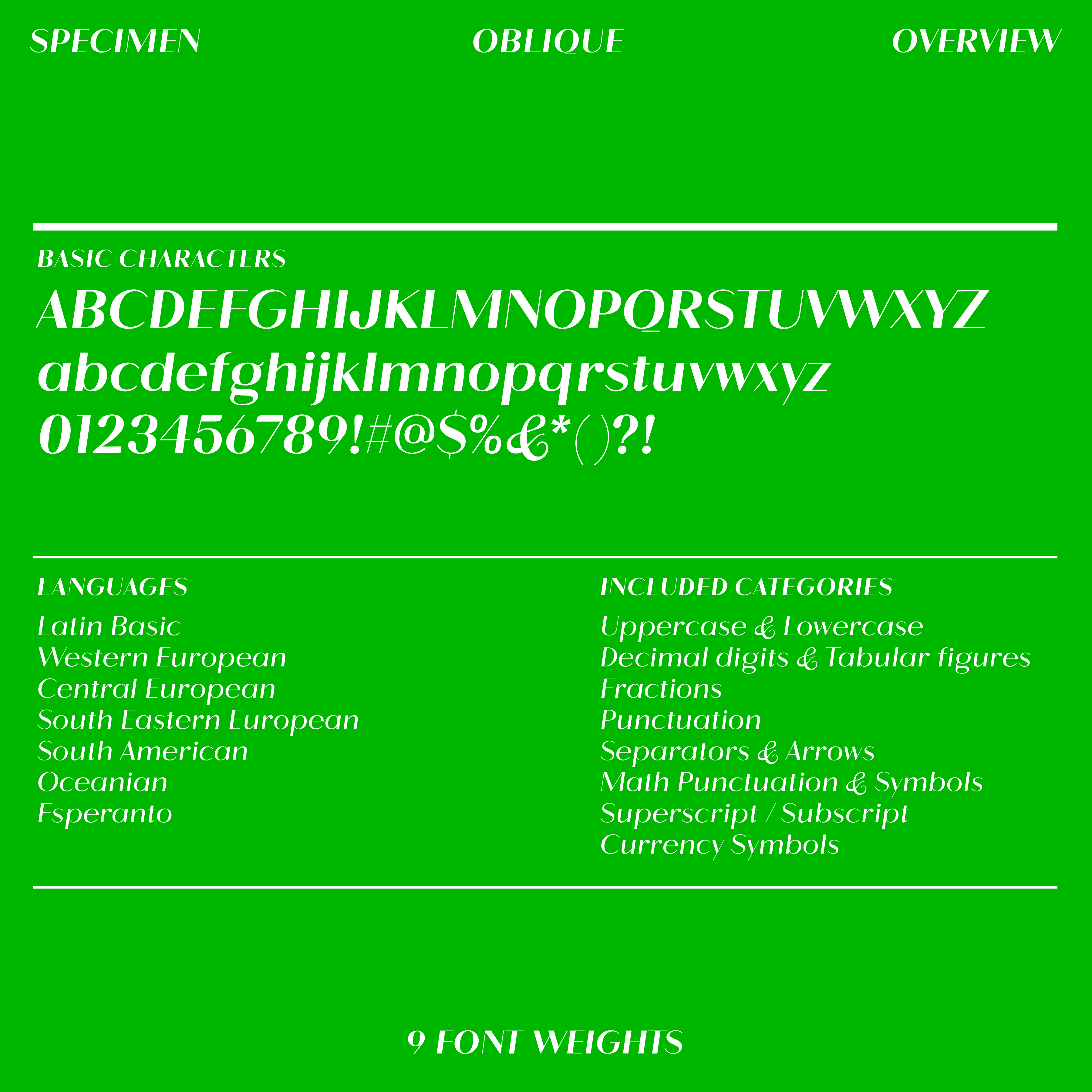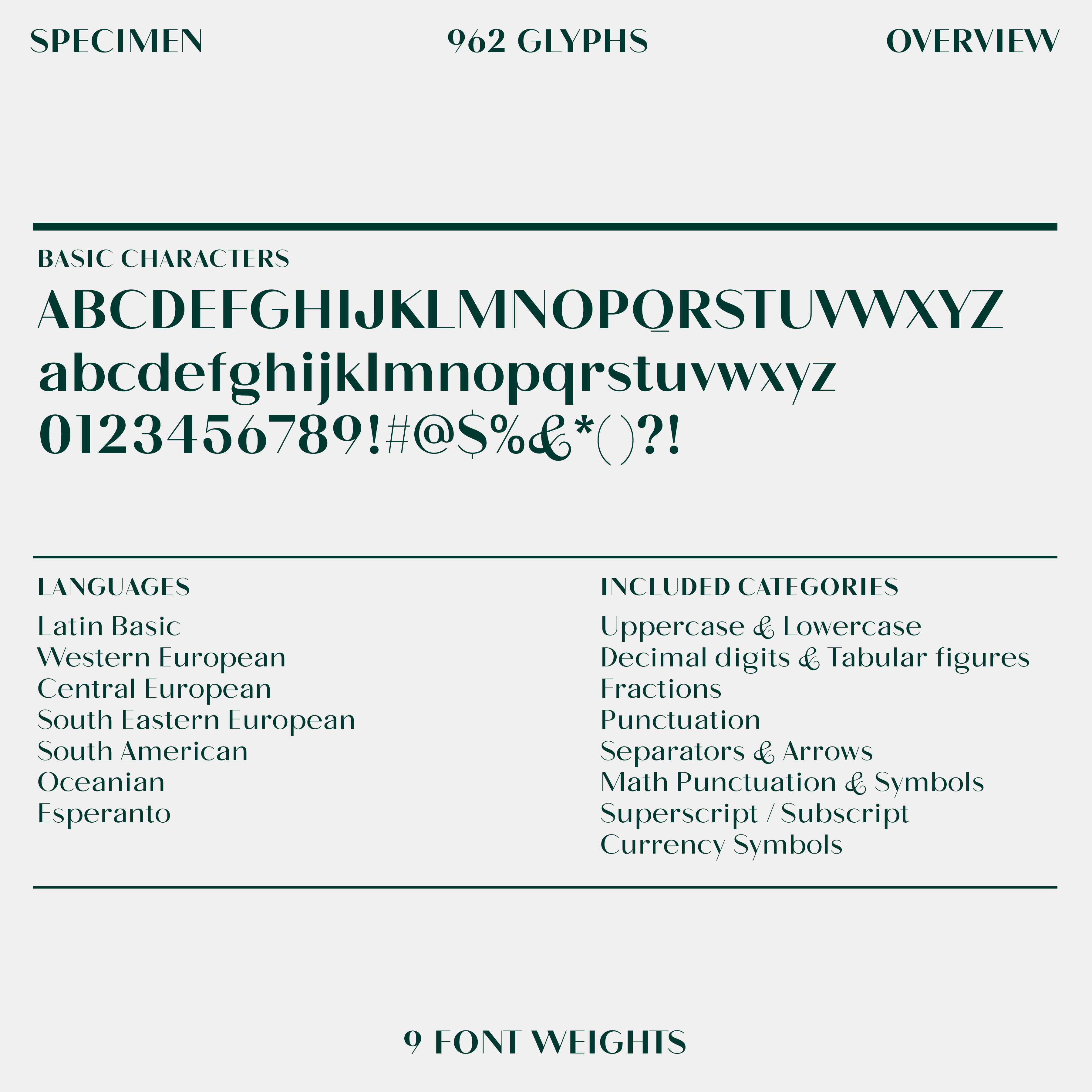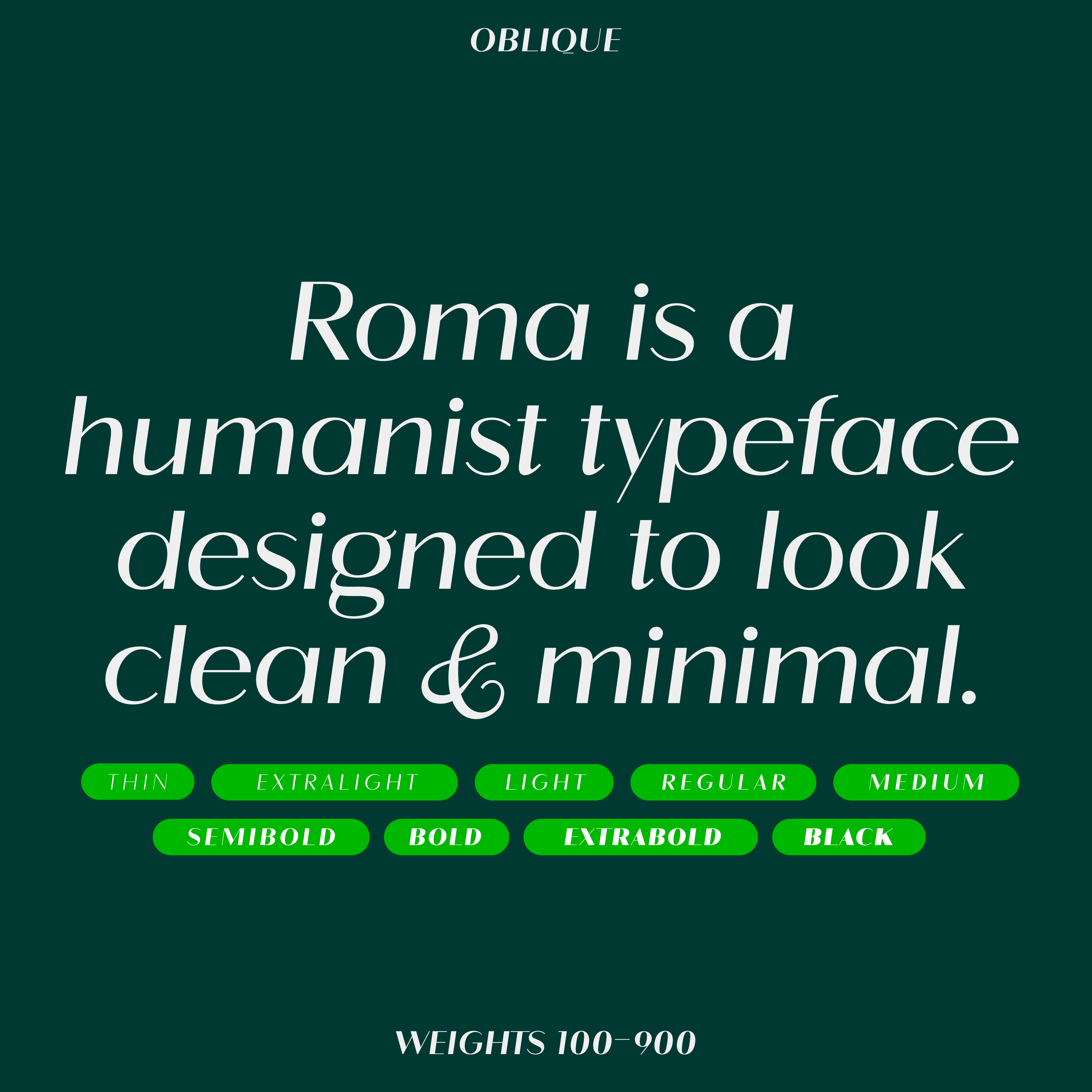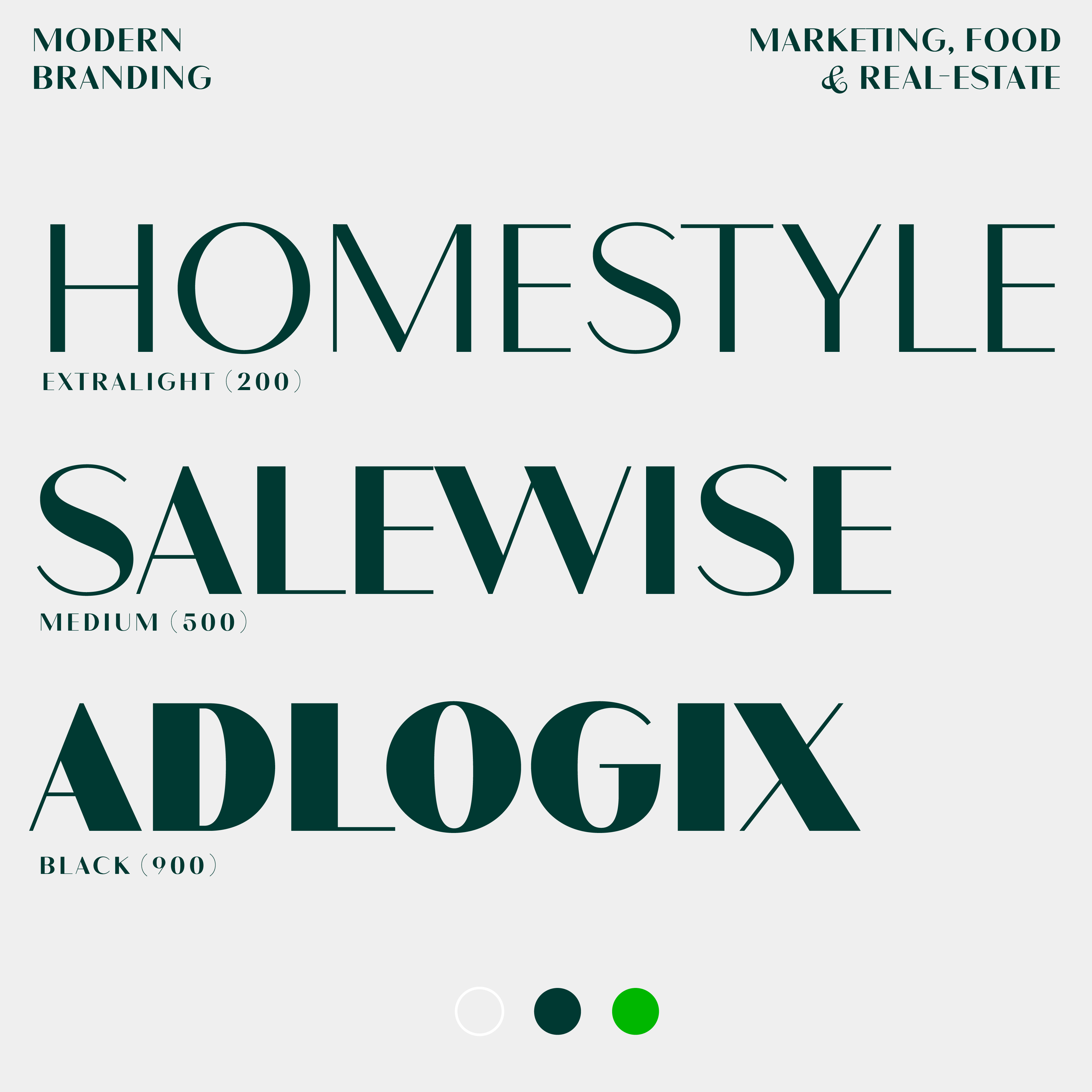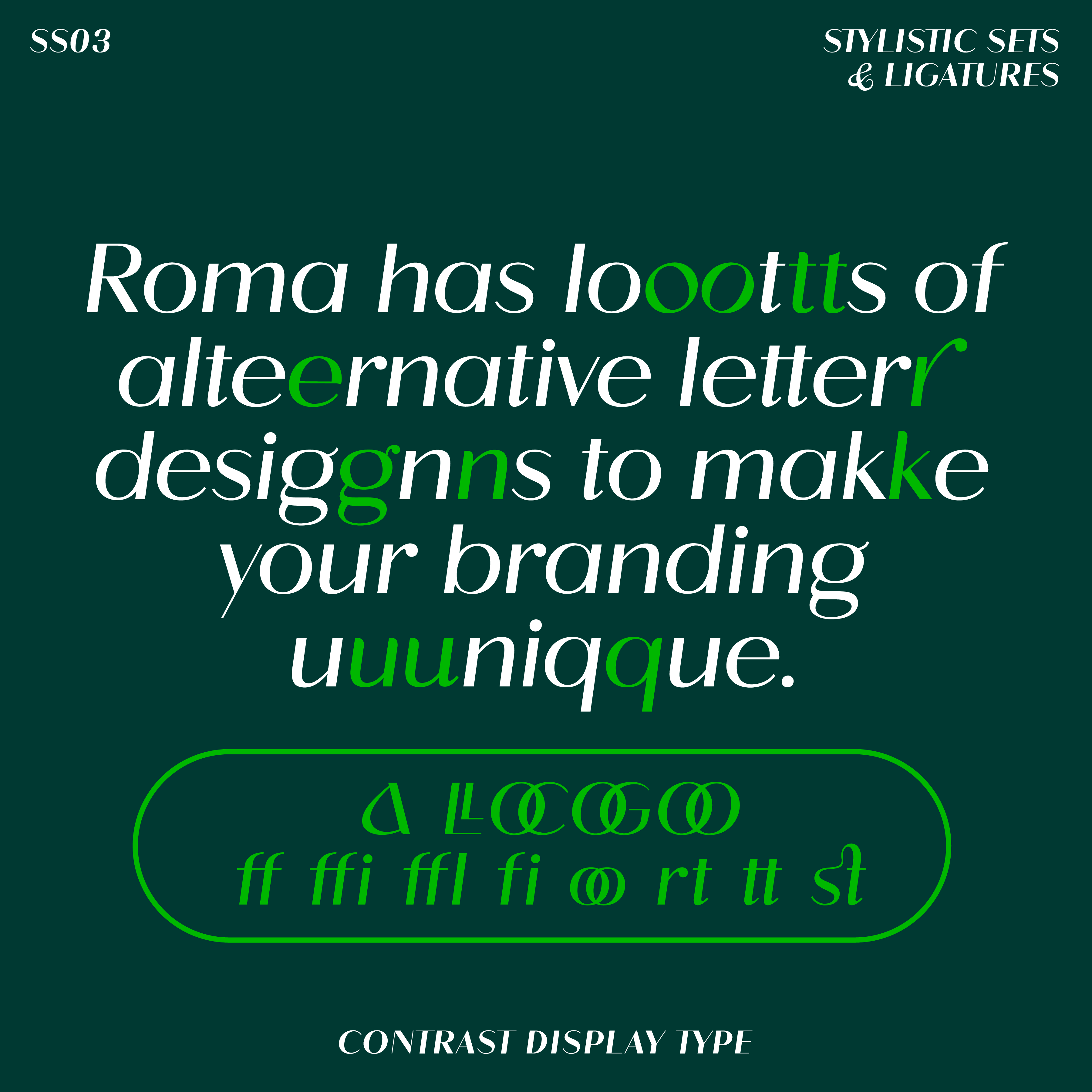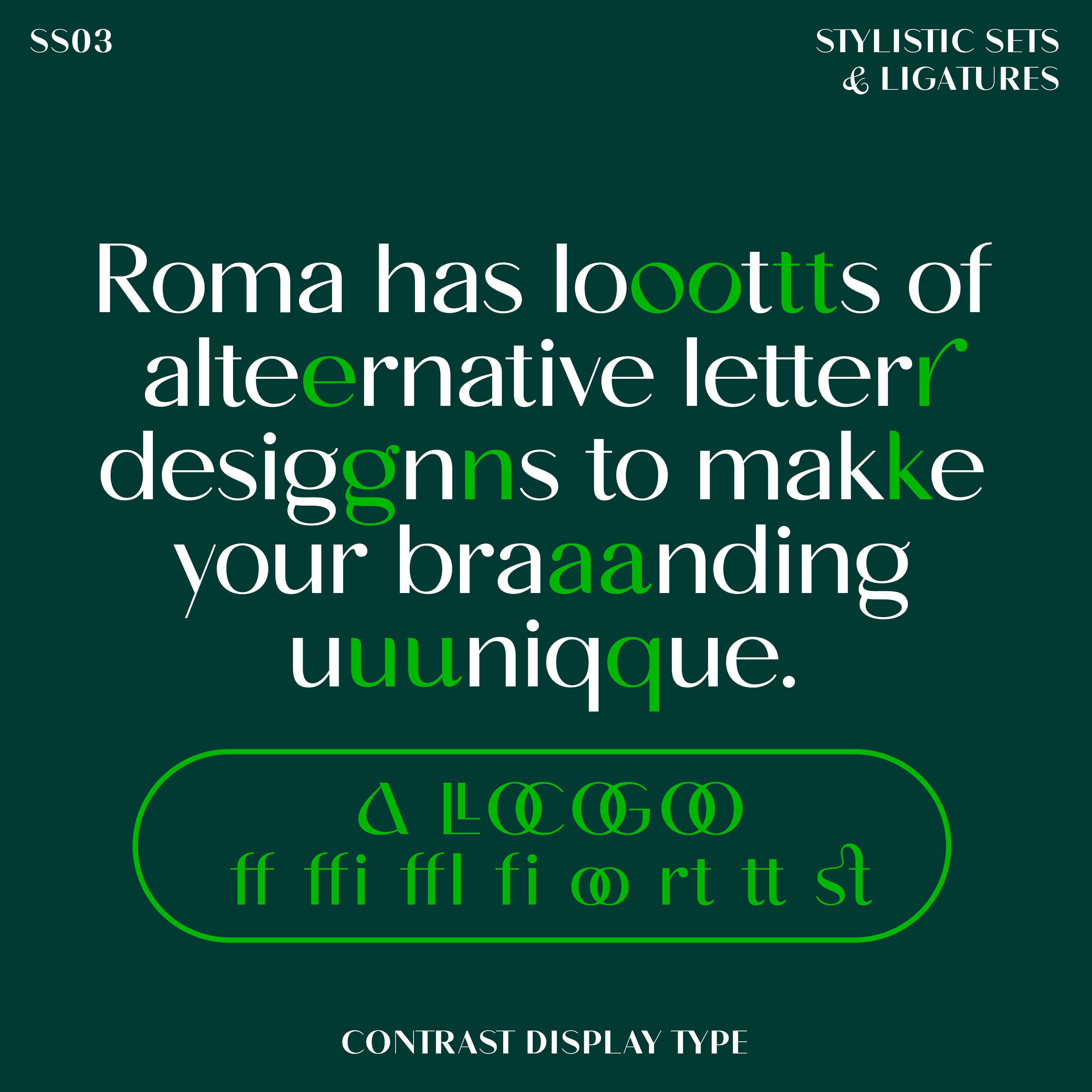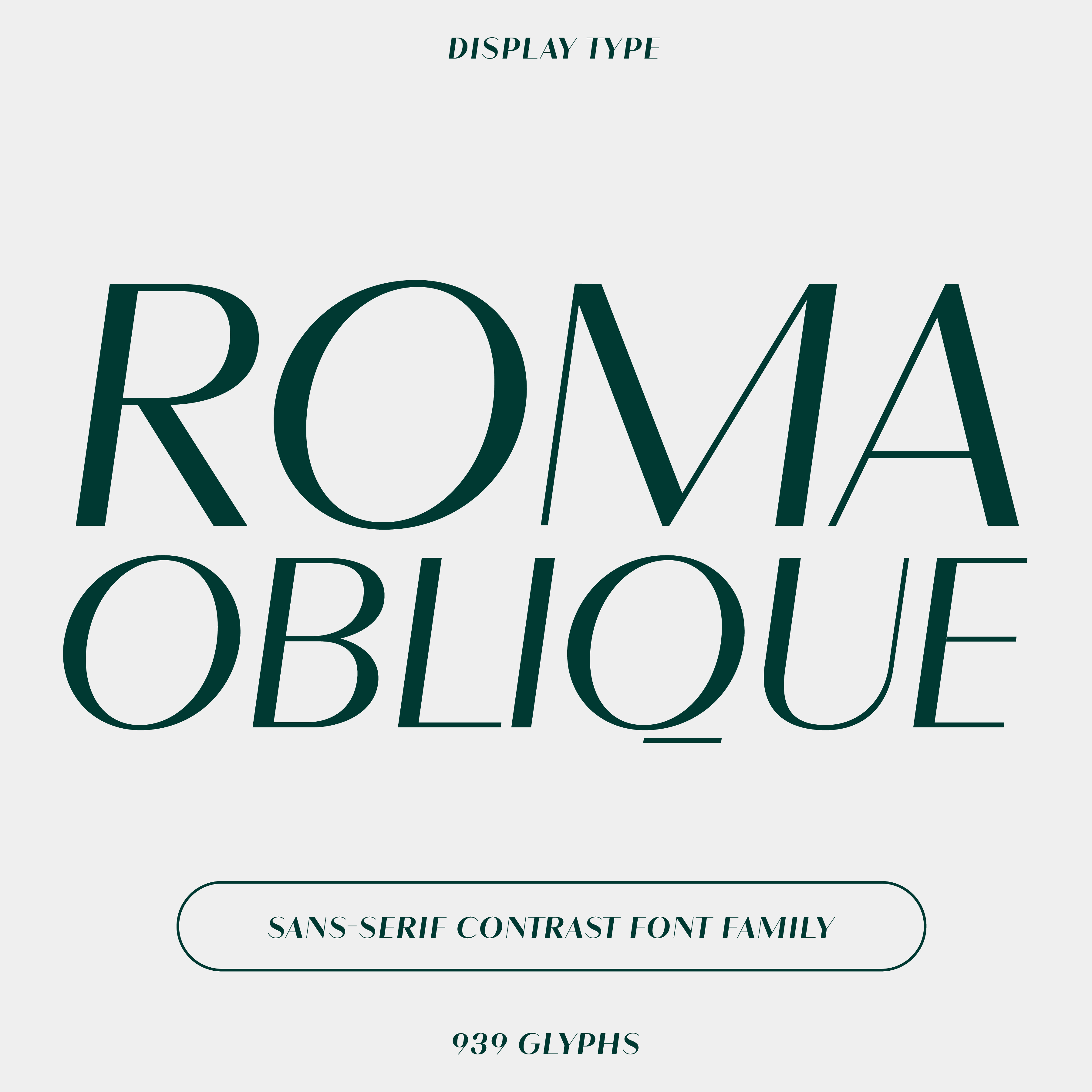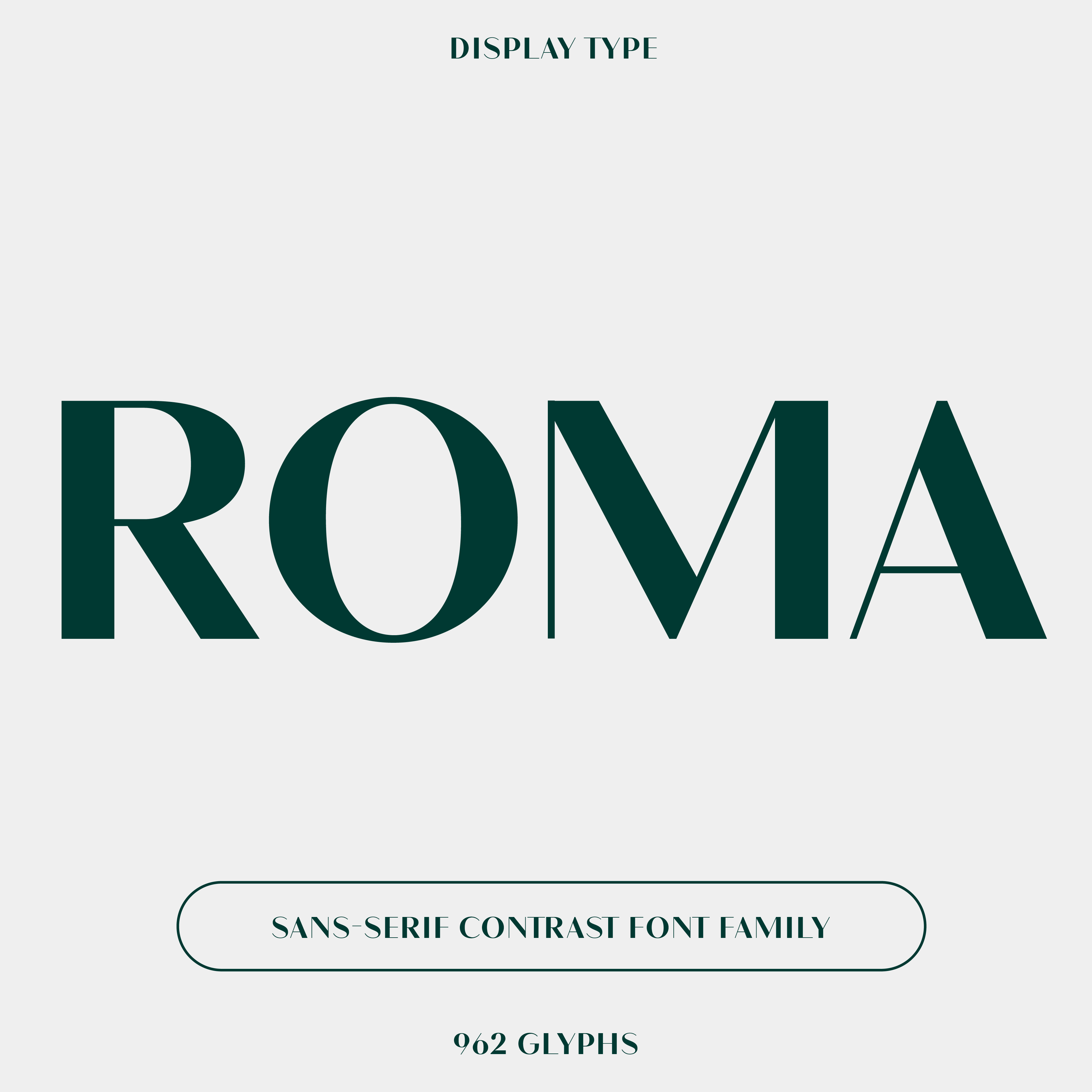
Roma: tipografía de contraste sin serifas  -
Roma: tipografía de contraste sin serifa (OBLIQUE)  -
Fuentes de lujo: Diseñe con clase utilizando nuestra colección
Incluso con los altibajos de la economía mundial, el mercado del lujo no solo sobrevive, sino que prospera. En 2023, alcanzó la increíble cifra de 1,5 billones de euros, lo que demuestra que el atractivo del lujo es más fuerte que nunca. Lea más aquí . La gente no solo compra artículos de lujo, sino que compra una experiencia, una muestra de un mundo que se siente exclusivo y refinado. Ya sea un automóvil de lujo, una estadía en un hotel de cinco estrellas o un bolso bellamente elaborado, el lujo consiste en adentrarse en algo especial.
En lo que respecta al branding, el lujo no se limita a los logotipos llamativos o los envases elegantes. Las fuentes que elija pueden marcar una gran diferencia en la sensación de lujo que transmite su marca. Por supuesto, un titular inspirador o una paleta de colores minimalista son fundamentales, pero la tipografía que elija (el estilo de las letras en sí) puede marcar el tono de forma sutil pero poderosa. Tanto si opta por letras de gran tamaño como por algo más minimalista y sobrio, la fuente adecuada puede llevar su mensaje a la excelencia.
En este artículo, analizaremos qué hace que una fuente se vea lujosa y le mostraremos cómo usar estas fuentes para que sus diseños se vean sofisticados y elegantes, tal como los productos de lujo que capturan los sueños de las personas en todo el mundo.
¿Qué define una fuente de lujo?
Fuentes serif: el arquetipo del lujo
Las fuentes serif se han asociado durante mucho tiempo con el lujo, la tradición y la sofisticación. La presencia de pequeños trazos al final de las letras agrega un elemento de refinamiento y herencia. Las fuentes como Quil y Mod de nuestra colección encarnan esta esencia lujosa con su apariencia clásica pero modernizada. Las fuentes serif pueden realzar una marca, dándole un aspecto atemporal y prestigioso. Combine titulares serif con textos de cuerpo sin serif para una imagen de marca más accesible.
Fuentes elegantes sin serifa
Si bien las fuentes serif transmiten lujo de manera natural, las fuentes sans-serif modernas pueden transmitir una sensación de extravagancia, especialmente cuando están diseñadas para mostrar fuerza y precisión. Las fuentes sans-serif más claras, como Scal y Soya de nuestra colección, ofrecen una interpretación contemporánea del lujo. La clave está en los detalles: terminales nítidas y barras abiertas y más amplias.
Pesos de fuente más ligeros
Los grosores de fuente más livianos suelen ser más elegantes y lujosos. Crean una sensación de sutileza y exigen la atención del espectador. Cuando se combinan con un espaciado considerado y tamaños de fuente más grandes, los grosores más livianos pueden transmitir una impresión asertiva sin resultar abrumadores. Considere Kijs para una fuente serif o Soya para una opción sans serif que incorpore esta ligereza.
Ortografía clásica y mayúscula
La elección de la ortografía, ya sea clásica o mayúscula, puede influir fácilmente en la percepción del lujo. La ortografía clásica tiende a evocar tradición, mientras que la ortografía mayúscula pide autoridad. En el diseño de lujo, la ortografía en minúsculas suele evitarse porque puede parecer informal.
Espaciado bien pensado y tamaños de fuente más grandes
Las fuentes de lujo requieren una consideración cuidadosa del espaciado: según sus objetivos, puede marcar la diferencia si el texto no es demasiado ancho ni demasiado informal, sino que tiene el tamaño justo. Este enfoque garantiza que el espectador sofisticado vea que la marca se preocupa por los detalles de la misma manera que lo hace con sus productos. Además, los tamaños de fuente más grandes pueden ser más lujosos porque permiten trazos más finos y elegantes, lo que aumenta aún más la sensación de refinamiento.
Paletas de colores monocromáticas y apagadas
El color es otra forma sencilla de transmitir lujo con un solo elemento de diseño. Las paletas claras y brillantes, como el blanco, el dorado y el plateado, son opciones tradicionales que demuestran exclusividad. Sin embargo, los tonos apagados como los pasteles, el negro, el gris oscuro y los verdes intensos también transmiten una sensación de lujo más discreta. Estos colores funcionan bien con fuentes como Edde y Rozi , y añaden profundidad y riqueza a tus diseños.
En una palabra
El lujo en la tipografía se basa en los detalles: desde la elección de fuentes serif o sans serif hasta la consideración cuidadosa del grosor, el espaciado y el color. Si comprende estos elementos y los aplica con cuidado, puede crear diseños que no solo parezcan lujosos, sino que también parezcan exclusivos y recuerden a las personas el cuidado que se le da a los productos de su marca. Ya sea que esté diseñando para una marca de moda de alta gama, un producto de belleza premium o un evento sofisticado, la fuente adecuada puede marcar la diferencia.